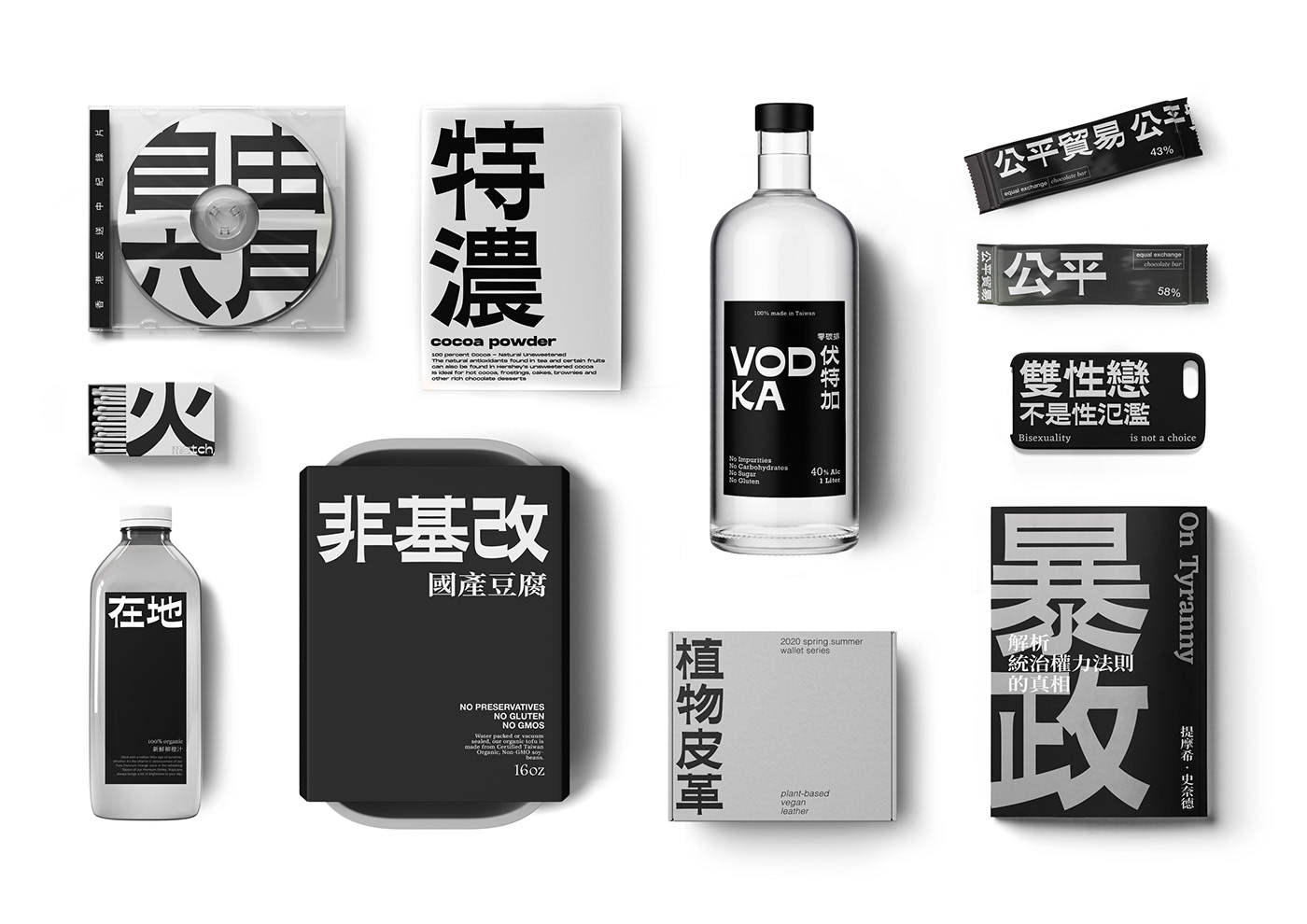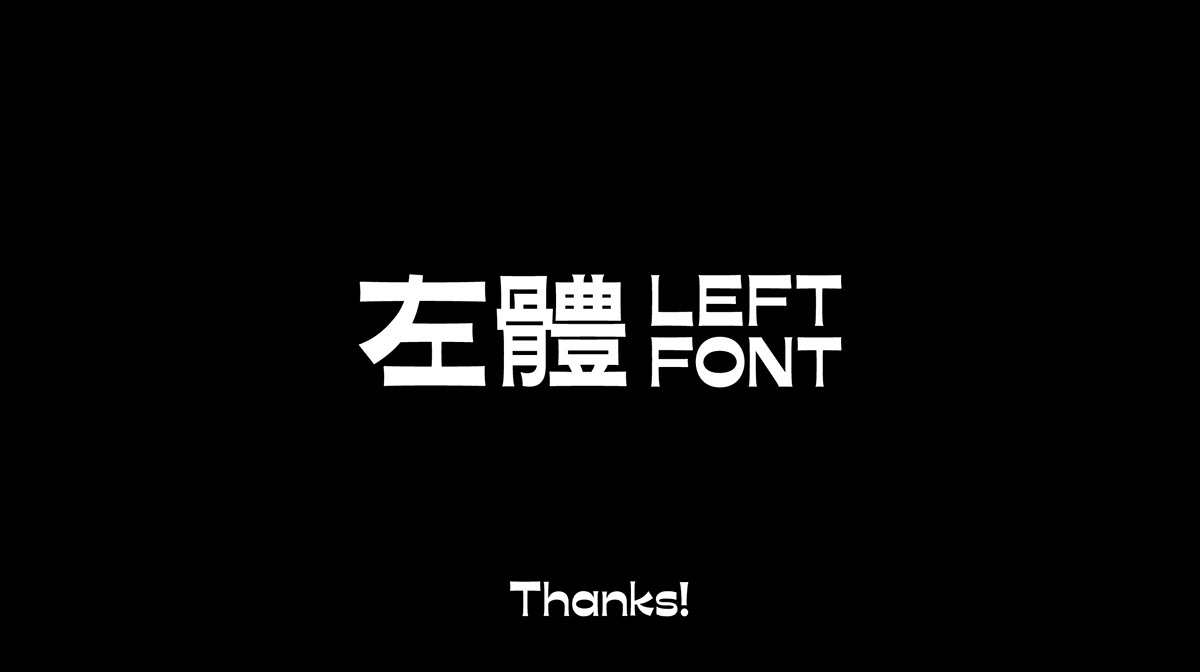
左體 Left Font
左體以叛逆精神作為出發點,是一款中文市場上極少見的逆反差字體——橫筆較粗而直筆較細,而橫筆反常的傾斜角度,蘊含了左手運筆的特徵。 左體的字面寬扁,筆畫粗細對比強烈,同時以柔和的曲線中和,使它顯得既顯眼、特別又不死板生硬,帶有人文味。除了中文以外,也設計了對應的歐文字母及數字,更加方便實用,適合被運用在任何表達主張的場合與文宣,例如選舉、社運,使用者在未來都能迎接屬於自己的自由民主。
Left Font, as a Chinese reverse contrast typeface which is quite rare in the commercial market, comes from the spirit of rebellion. The characters' horizontal strokes are thickened while vertical strokes are narrower. Furthermore, the unusual tilting angle of the horizontal stokes shows the features of the handwriting of a left-handed.
Left Font has a wide and flat outlook with both strong contrast of thickness and soft curves. It brings out an impressing and artistic style, yet not so rigid. Besides Chinese characters, Latin letters and numbers with the same style are also available in Left Font, so that it can be widely used in a variety of circumstances including elections, social movements and so on.